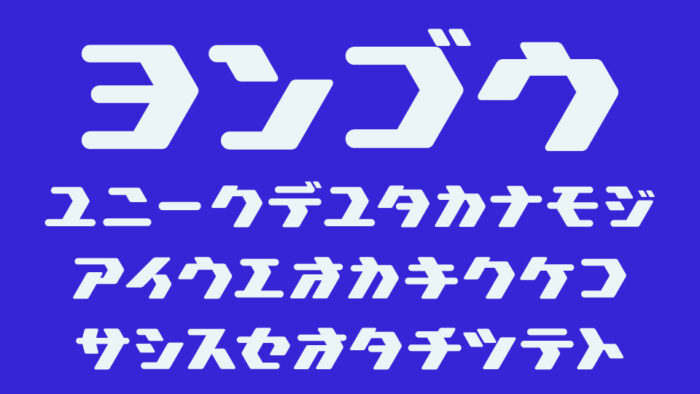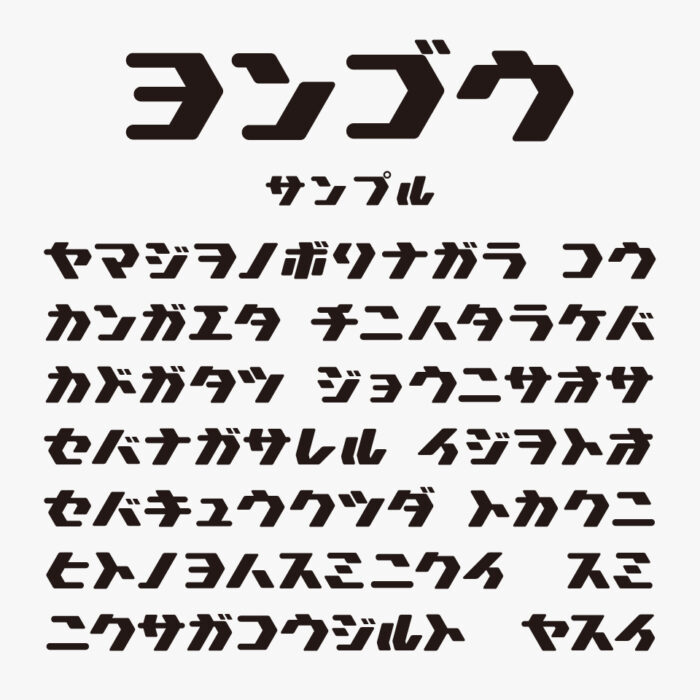
IKヨンゴウフォントは、無骨さと近未来感を併せ持つ角張ったカタカナフォントです。
エッジの効いた直線と斜めのラインで構成されており、スピード感やエネルギーを感じられるデザインです。ロボットや機械に書いているロゴのような雰囲気をもちシャープさのあるかっこいいフォントです。
IKヨンゴウ
収録文字は、カタカナが収録されています。
ひらがな×
カタカナ○
漢字×